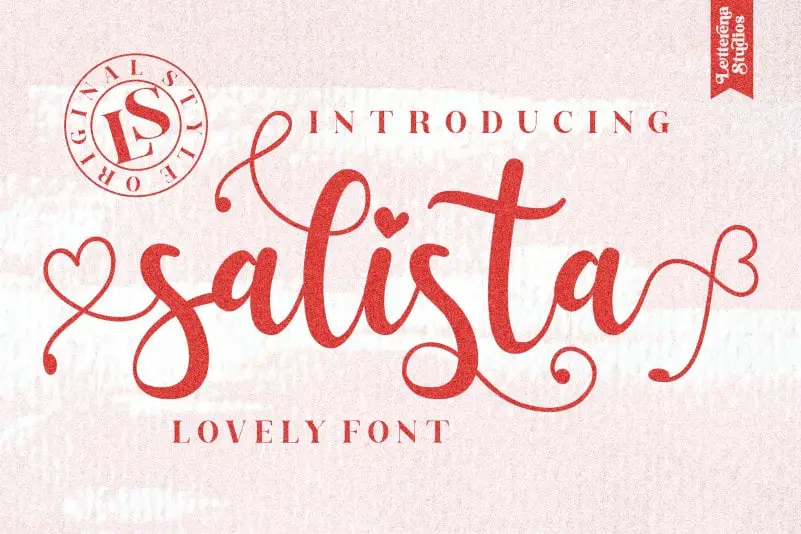
Salista Script Font – Fonte Grátis
Salista Script Font
A Salista Script Font é uma elegante fonte feita à mão que captura a delicadeza do estilo script. Suave e encantadora, esta fonte se destaca como um recurso ideal para projetos românticos e personalizados, como convites de casamento ou cartões. Ela possui um conjunto impressionante de símbolos únicos e leves que se movem com suavidade, permitindo a criação de texturas efeitos vibrantes em qualquer projeto gráfico, sem esforço algum. A PUA Encoding da fonte permite que você explore facilmente todos os detalhes belamente projetados desta fonte elegante. Seja para um design pessoal ou comercial, o Salista Script Font é uma escolha perfeita para adicionar um toque suave e encantador aos seus trabalhos visuais.